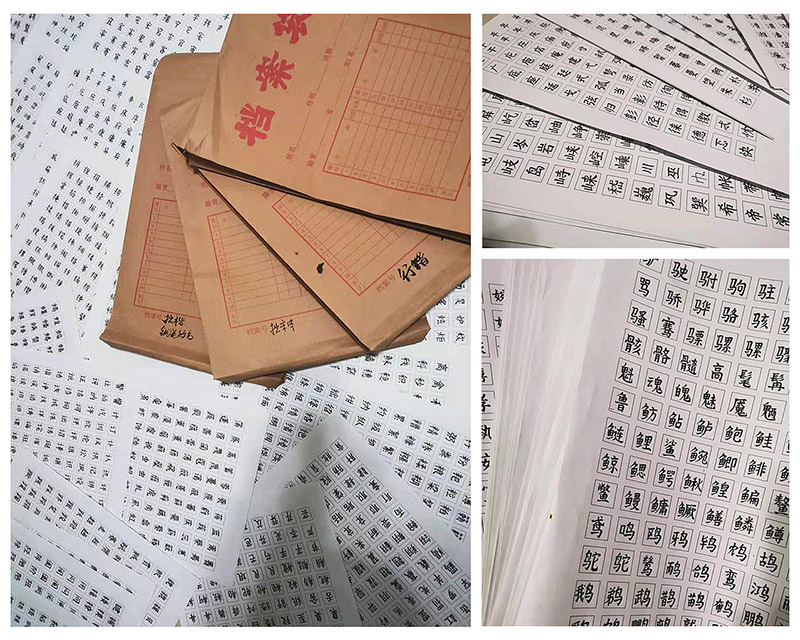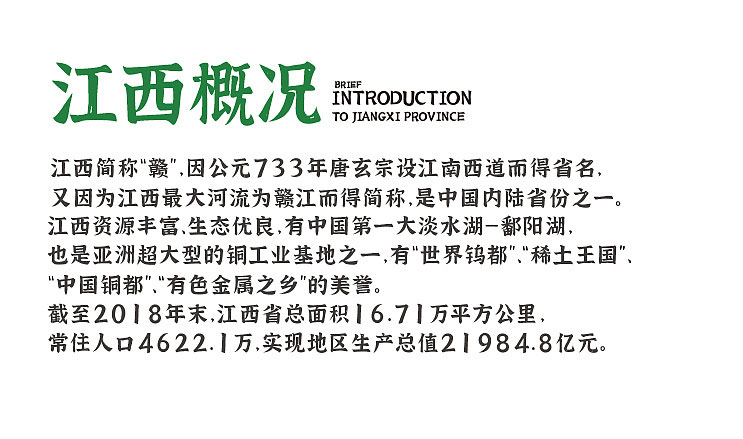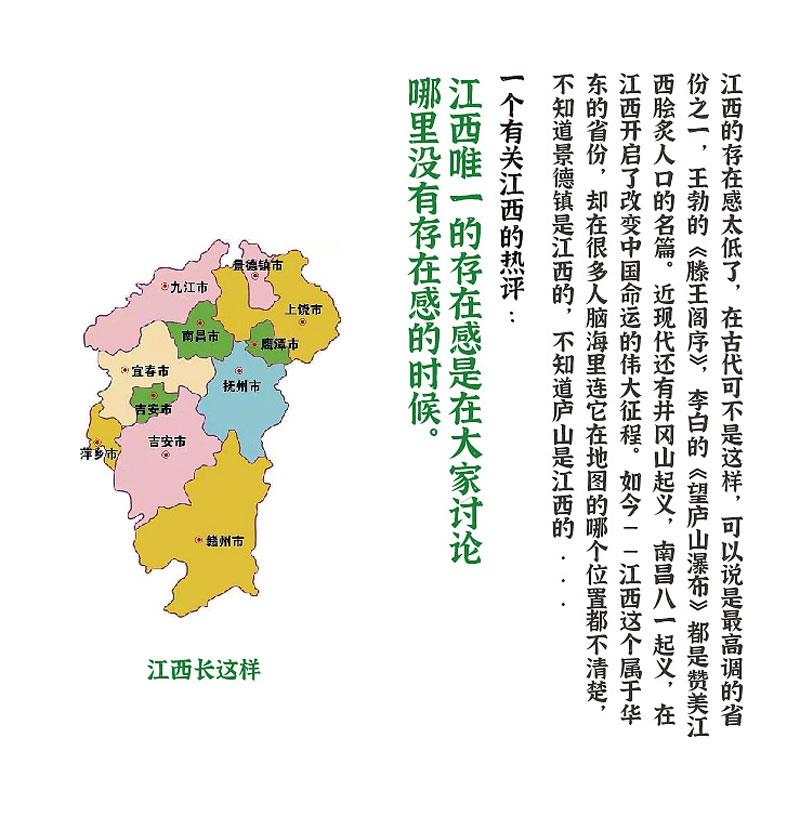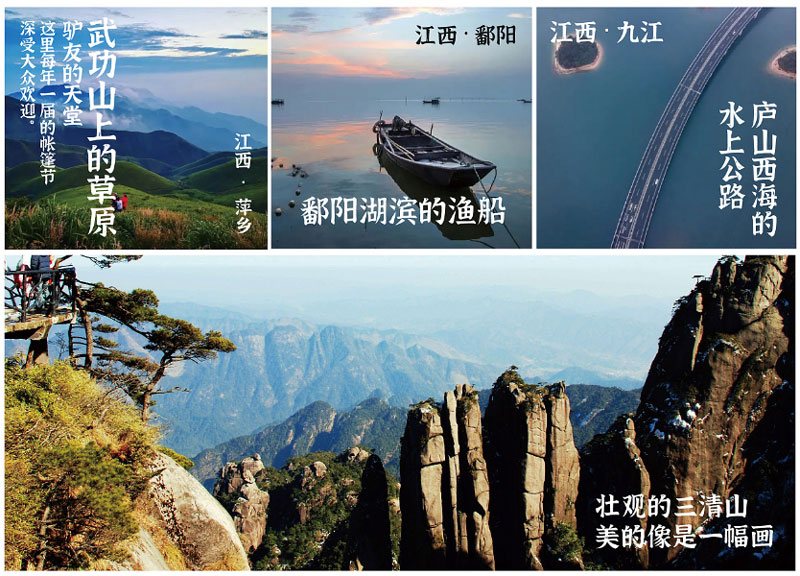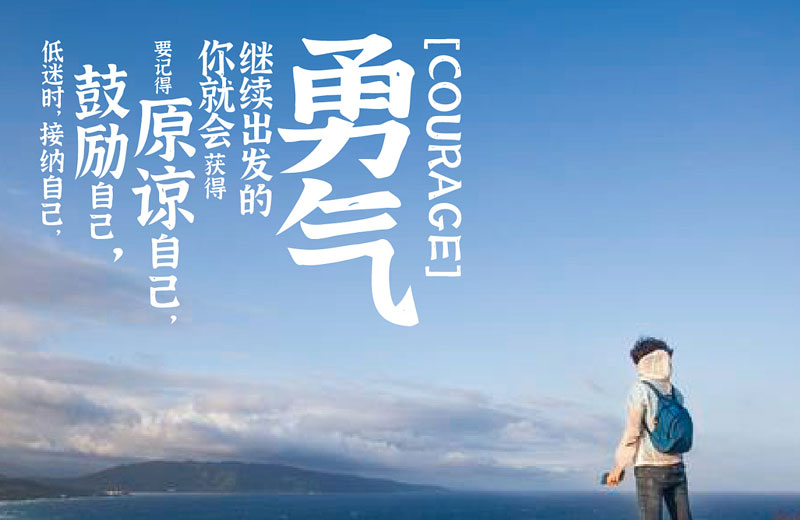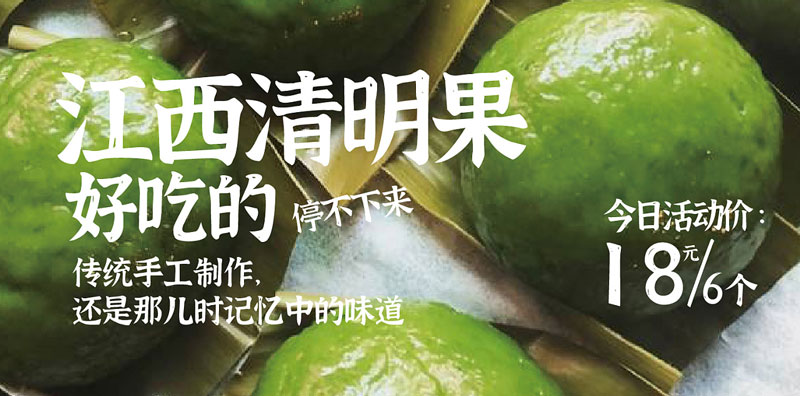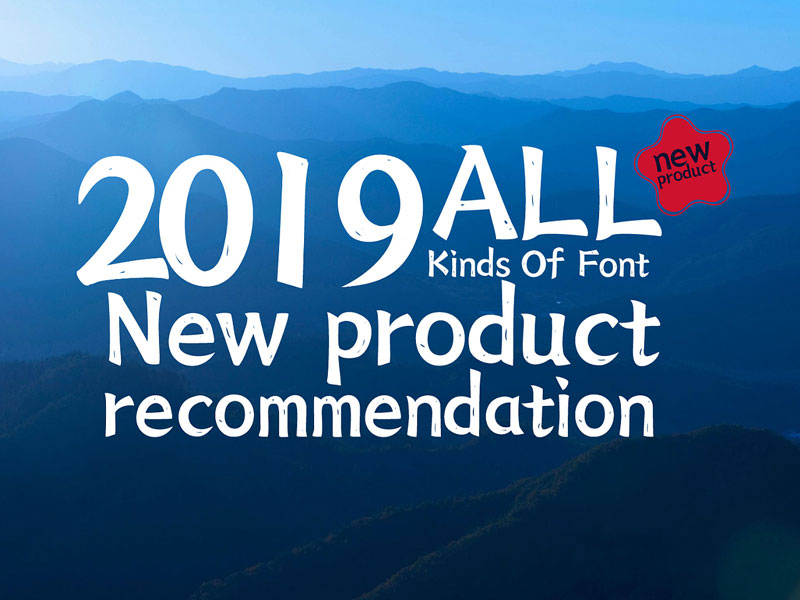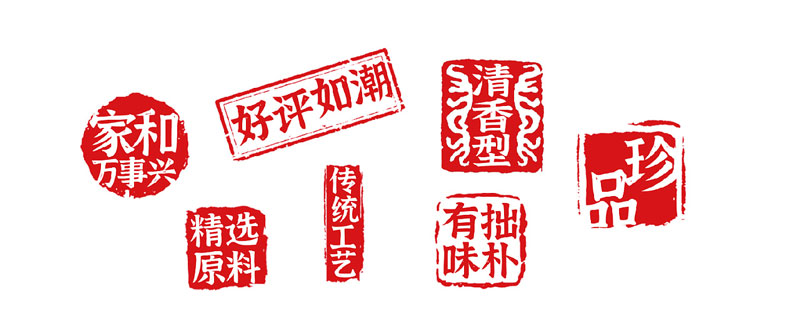
江西拙楷手写楷体,免费可商用
「江西拙楷」是由字体设计师黄煜臣用半年时间独立制作完成,对于这款字体的发布,黄煜臣不希望仅仅就是一款字体的展示,希望它能发挥更大的作用,带来一些其他的价值,最终决定用这款字体为我们大江西做宣传,并且用自己家乡的名字命名
「江西拙楷」是一套手写楷体,相比电脑中标准化制作的楷体,这套字体的笔画会带有一些书写的痕迹,每个字的笔画是没有统一标准的,所以看上去显得不够规范,但是会有一种手写的自然之感。